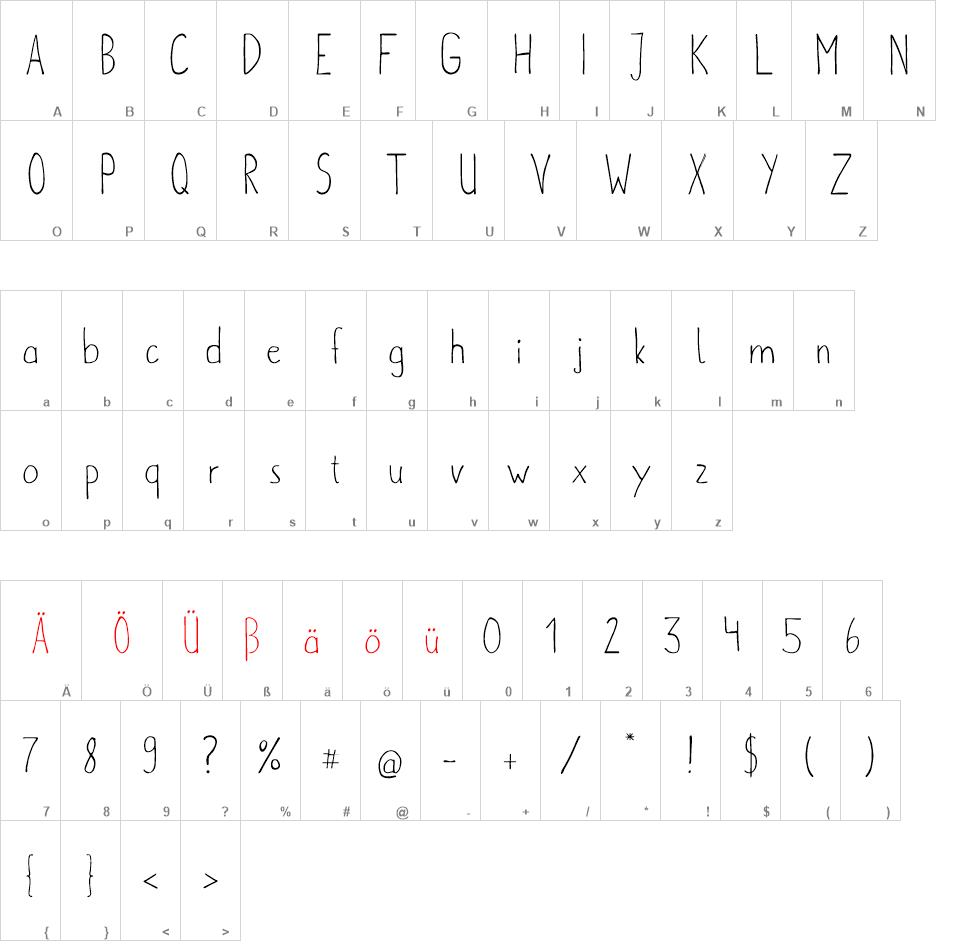
Metafors
Metafors font
Metafors
Eine Handschriftschrift. Ein wenig ungeschickt, authentisch und leicht. Absolut frei für kommerziellen und persönlichen Gebrauch. Verrückt werden! :-)